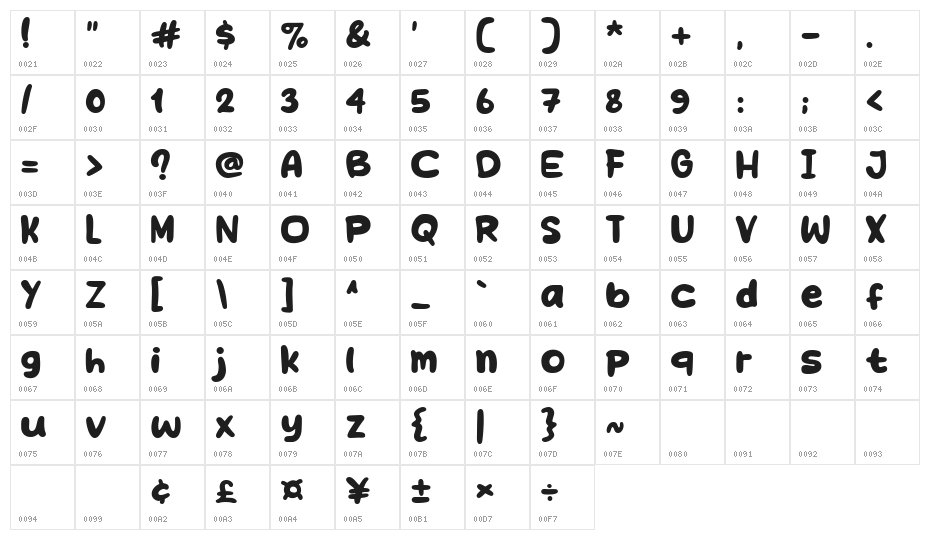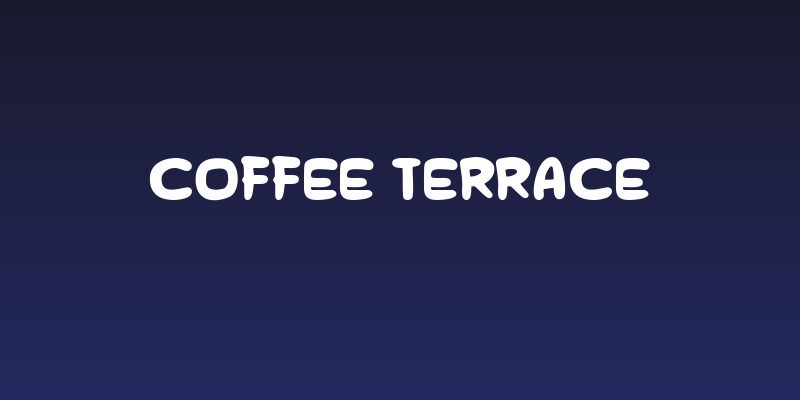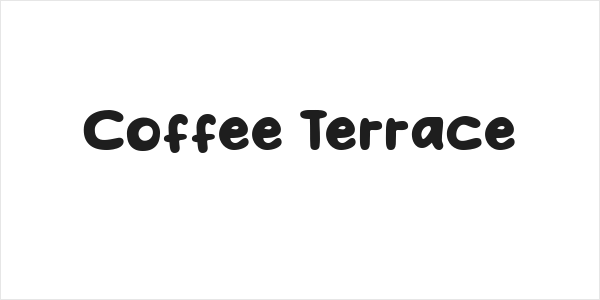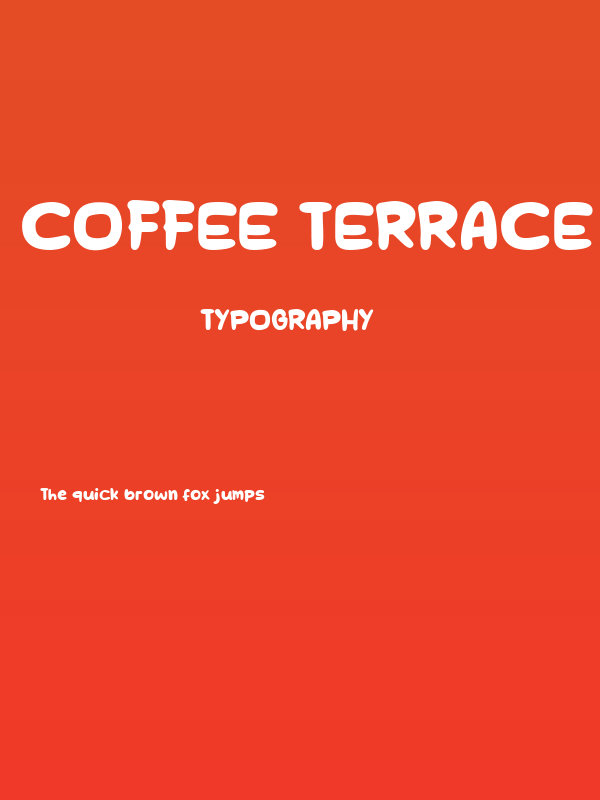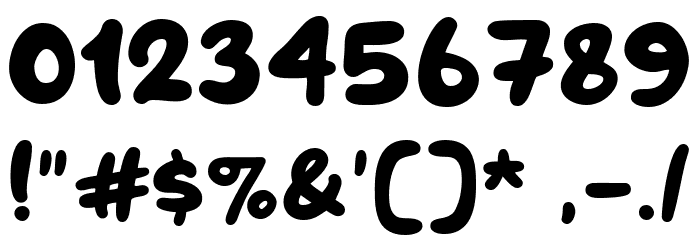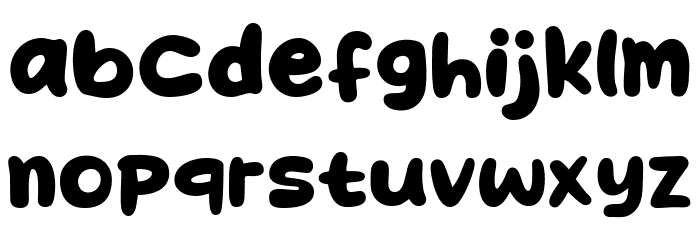
Coffee Terrace Font
| النمط العام | Playful, Informal |
| مشاريع مقترحة | Ideal for children's books, playful branding, party invitations, and casual social media graphics. |